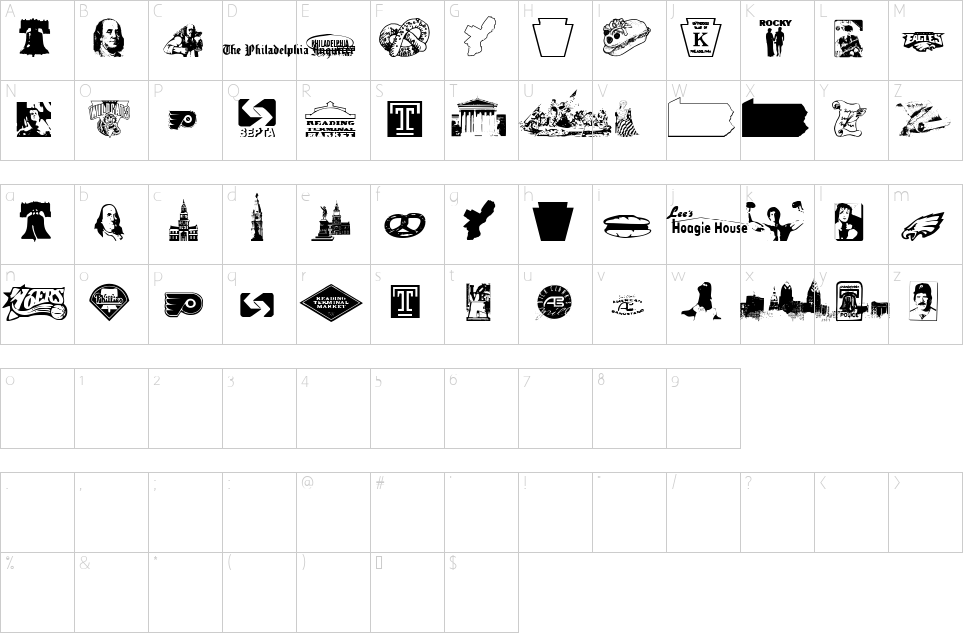
Descubra a Philadelphia Dings font, uma opção de fonte icônica disponível gratuitamente para Windows e Mac. Esse design foi criado pela Iconian Fonts e já foi baixada por 2.498 usuários. Philadelphia Dings é perfeitamente adequada para adicionar um toque único em projetos digitais. Com uma aparência elegante e elegante, esta fonte é uma ótima opção para designers gráficos, especialmente para aqueles buscando uma fonte sem ser muito chamativa. Com Philadelphia Dings, você pode explorar uma variedade de estilos, desde elegantes headlines até letras mais legíveis para conteúdo informativo. Não perca esta oportunidade de ter essa fonte poderosa em seu arsenal de design.